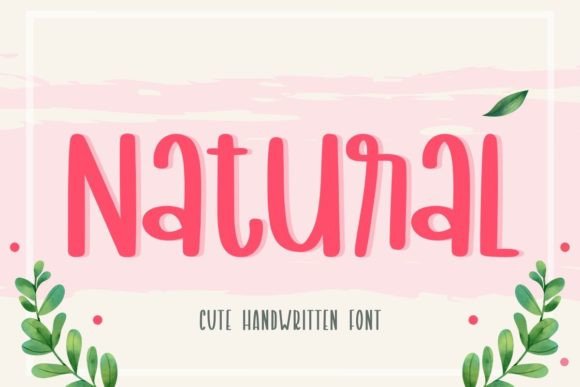
Natural
Việc tìm kiếm các thành phần thiết kế phù hợp có thể là một thách thức, nhưng Natural cung cấp một bộ sưu tập đặc biệt giúp nâng tầm công việc của bạn ngay lập tức.
Được chế tác với độ chính xác cao, Natural cung cấp các vector sạch, kiểu chữ mượt mà và giấy phép thương mại để bạn yên tâm.